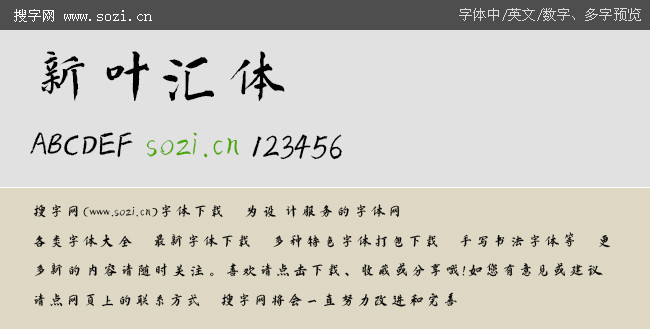
新葉匯體
搜字網(wǎng)給大家提供一款新葉匯體中文手寫書法字體下載,新葉匯體由新葉傳媒制作,簡(jiǎn)體+符號(hào)共計(jì)7123字,字體看上去肆意灑脫,如流水一樣帶動(dòng)著流動(dòng)的氣息,卻形動(dòng)而神不散,展示了匯的精髓。。適用于大標(biāo)題、包裝設(shè)計(jì)、海報(bào)設(shè)計(jì)等應(yīng)用。【此款字體可供個(gè)人非商業(yè)免費(fèi)使用,商用請(qǐng)關(guān)注公眾號(hào)“新葉傳媒”進(jìn)行購(gòu)買使用】